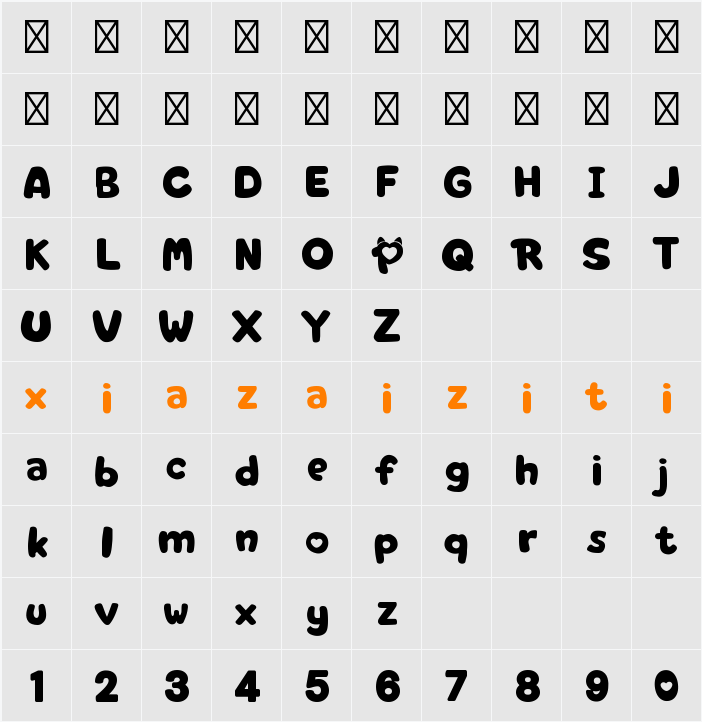
Wonderful Fonty Cure!
Wonderful Fonty Cure!,这款字体结构工整、笔画清晰,兼顾美观与易读性,适用于标题、正文、海报、包装、LOGO 等多种场景。字形优雅稳定,风格百搭耐看,适配日常排版与创意设计,让文字呈现更舒适、更具质感。Wonderful Fonty Cure!一笔一画,皆是细节,以均衡的比例、流畅的线条打造舒适视觉体验,字形端正大气,风格简约现代。无论是商业设计、品牌宣传还是日常排版,都能轻松驾驭,让文字更有格调与力量。Wonderful Fonty Cure!字体下载。